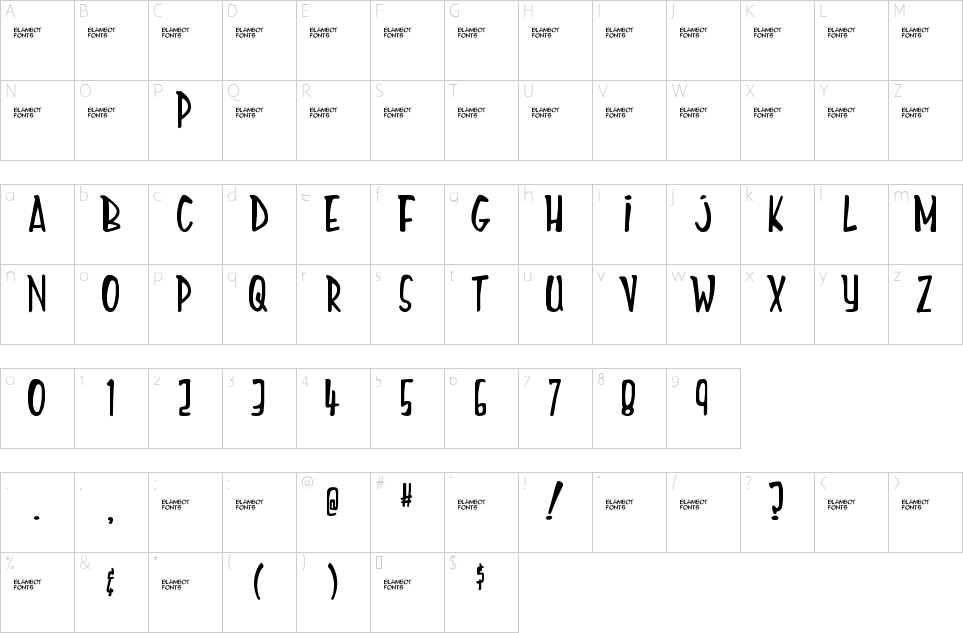
A Mighty Tomato font é uma opção divertida e vibrante para estilos de texto modernos. Desenvolvida pelo designer independente Blambot Fonts, esta fonte está disponível para download tanto para sistemas Windows quanto Mac. Com suas linhas redondas e suas cores alegres, ela é perfeita para criar efeitos de texto atraentes e únicos. Mais de três mil pessoas já aproveitaram a beleza desta fonte em suas criações. Engajante, agradável e versátil, a Mighty Tomato font é uma ótima escolha para quem busca algo novo e colorido para seus projetos de design.